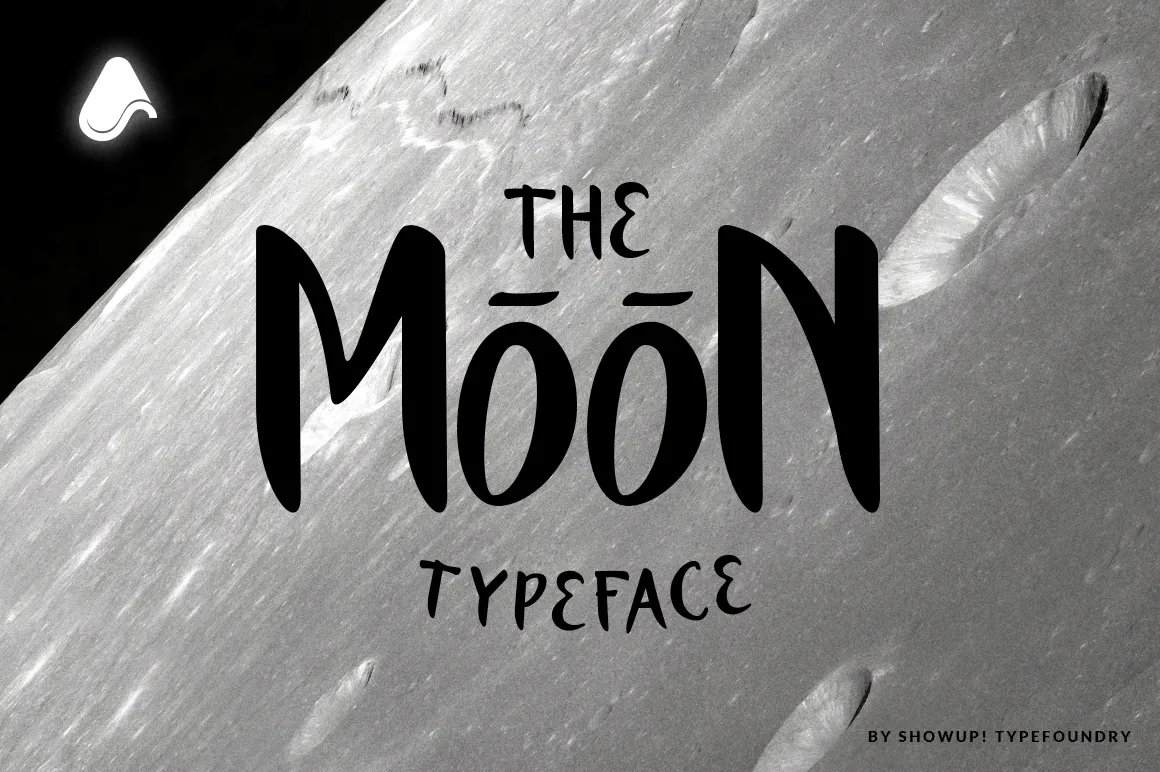
The Moon Typeface – Download Grátis
Introduzimos The Moon Typeface! Designada pelo próprio Aulia Rahman, The Moon é uma tipografia de traços manuscritos perfeitamente adaptada para logotipos, frases de efeito, convites e muito mais. Um elemento único e encantador que pode transformar qualquer design em um destaque. A The Moon oferece várias variações por caractere, incluindo alternativas aberturas, ligaturas comuns e até mesmo swashes adicionais para que você possa personalizar seu projeto conforme necessário. Perfeito para uso em logotipos, cartão de visita, posters, design de roupas, etiquetas e muito mais. Esta fonte é ideal para quem busca um elemento diferenciado para seus projetos. Seja para adicionar um toque pessoal a seu logo ou personalizar sua newsletter com uma frase encantadora, The Moon está aqui para ajudar. Não hesite em experimentá-la; você não vai se arrepender!